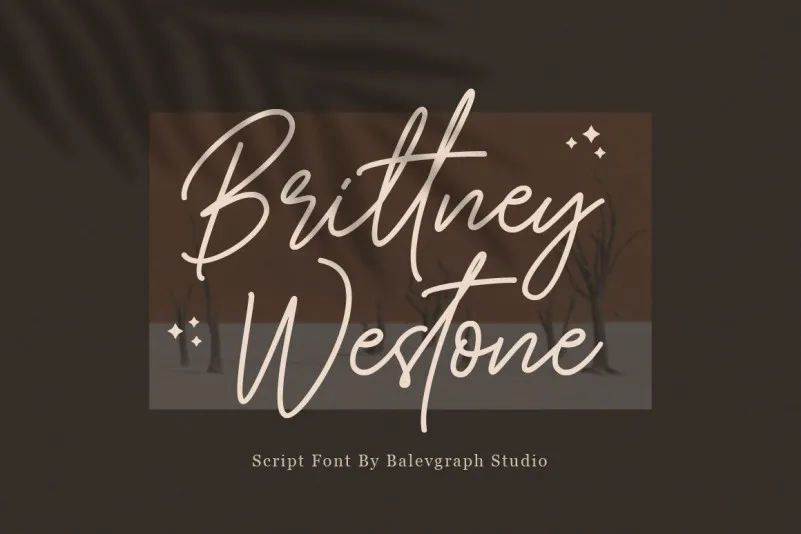
Brittney Westone Font – Download Grátis
Esta fonte é resultado de uma autêntica escrita a mão com características naturais, criada pelo designer Balevgraph Studio através da 99designs. O seu estilo sedutor se destaca como uma opção ideal para criar cartões de convite para casamentos deliciosamente bonitos e artesanais, arte elegante em estaçãoaria e postagens sociais impactantes. Seja você um designer gráfico ou criador de conteúdo digital, esta fonte é perfeita para adicionar um toque especial a qualquer projeto que precise de uma personalidade única e natural.